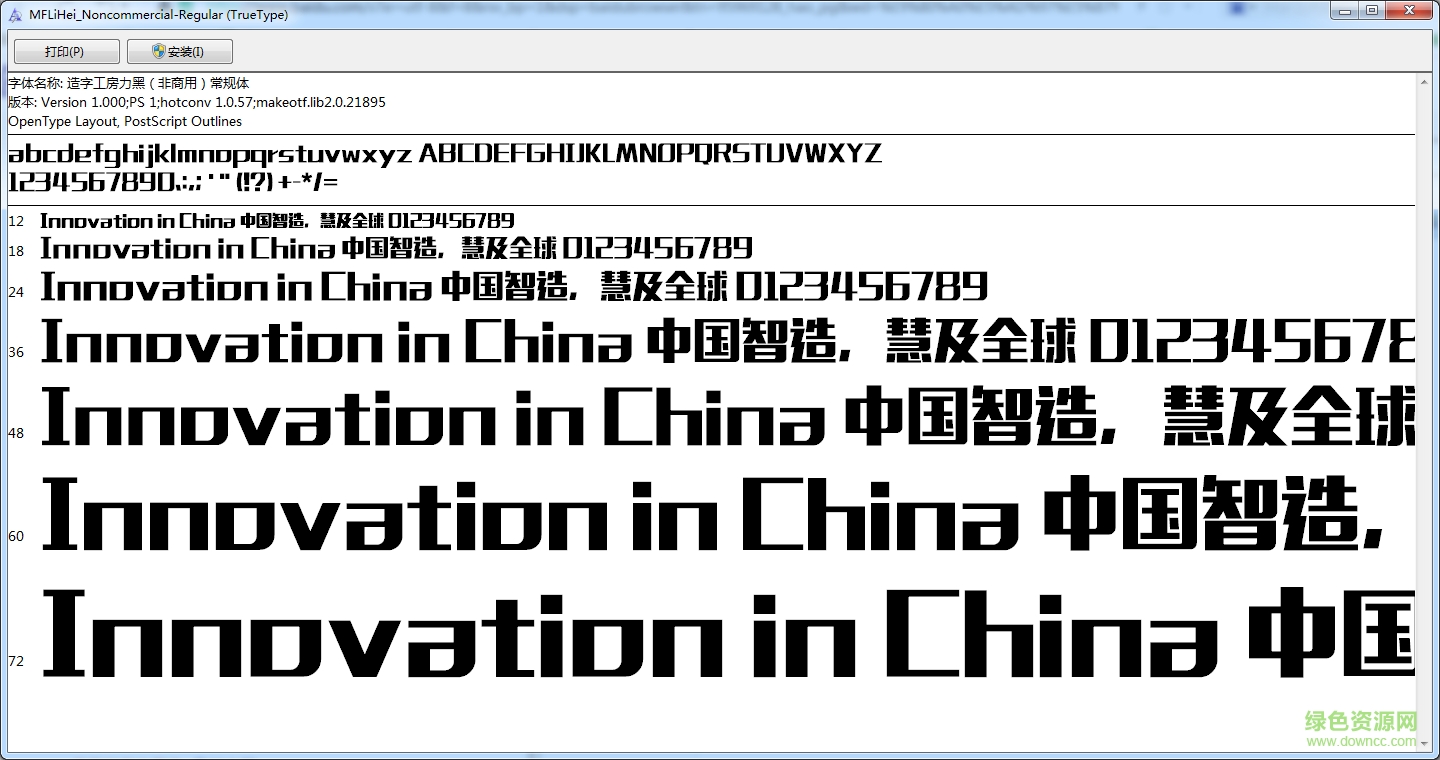
軟件介紹 軟件標(biāo)簽: 造字工房力黑體 造字工房 造字工房力黑體是一款常用的中文簡體字體,此款字體線條粗實,結(jié)構(gòu)簡潔,具有易讀性高,引人注目等特點,廣泛的應(yīng)用于平面設(shè)計、廣告設(shè)計、排版印刷等各行各業(yè),需要的朋友歡迎來綠色資源網(wǎng)下載!字體安裝方法方法一:控制面板/字體/文件/安裝新字體;方法二:直接將字體復(fù)制到C:\WINDOWS\Fonts。方法三:針對win7系統(tǒng),用戶只需選中字體右鍵安裝即可。注意事項本站所有字體資源僅供個人學(xué)習(xí)與參考,如需商業(yè)使用請到相關(guān)官網(wǎng)授權(quán) 軟件截圖 上一張下一張(1 / 1) 安裝詳細(xì)截圖 猜你喜歡 造字工房 造字工房 造字工房字體是一系列簡潔美觀的字體,小編為大家?guī)砹硕嗫畛S米煮w,覆蓋了常規(guī)體、黑體、情書體等,整體效果甚是出色,全部均為ttf格式,可直接安裝導(dǎo)入至ps中使用,方便用戶日常使用。 查看更多>> 造字工房力黑非商用常規(guī)體ttf 766KB/中文/2.0/下載 造字工房妙妙字體 3.03M/中文/10.0/下載 造字工房丁丁手繪字體 2.86M/中文/10.0/下載 造字工房勁黑常規(guī)體 694KB/中文/2.0/下載 造字工房朗倩字體 1.07M/中文/2.9/下載 造字工房朗宋(非商用)常規(guī)體 1.00M/中文/6.6/ttf版下載 其他版本下載 標(biāo)題 大小 更新日期 下載 下載地址 電腦版 造字工房力黑非商用常規(guī)體ttf 點擊報錯 軟件無法下載或下載后無法使用,請點擊報錯,謝謝! 關(guān)閉報錯反饋 請描述您所遇到的錯誤,我們將盡快予以修正,謝謝! *必填項,請輸入內(nèi)容 本類最新 dreamweaver字體庫 首爾南山體字體 v1.06 官方版 潮字社風(fēng)云簡ttf 潮字社凌渡鯤鵬簡體字體 潮字社曾玉波手書簡字體 微博慧心字體 用戶評論 熱門評論 最新評論 發(fā)表評論 查看所有評論(0) 昵稱: 請不要評論無意義或臟話,我們所有評論會有人工審核. 字?jǐn)?shù): 0/500 (您的評論需要經(jīng)過審核才能顯示)